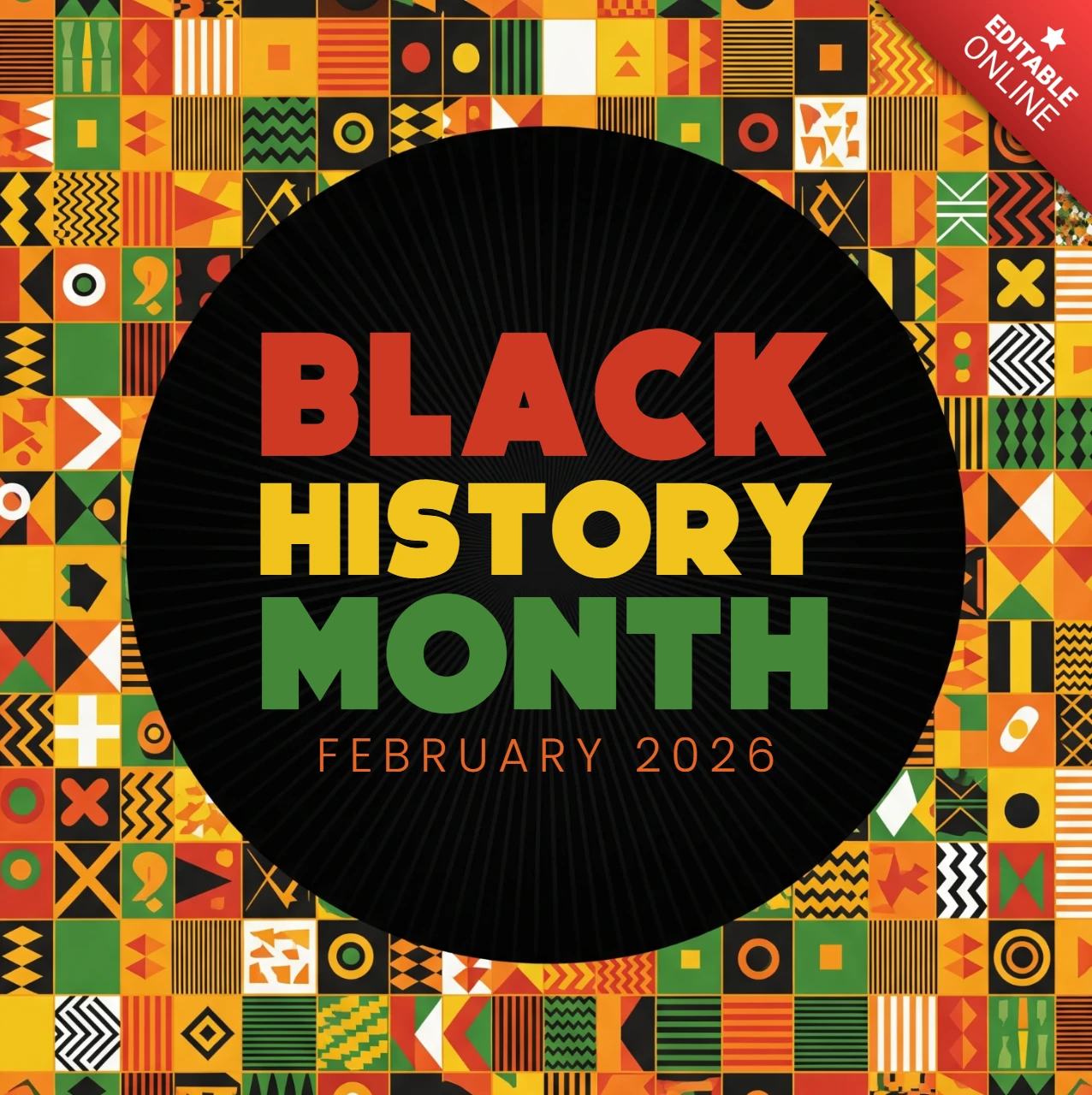
Affiche du mois de l'histoire des Noirs 2026 avec une typographie audacieuse dans des couleurs panafricaines, un cercle central et des bordures géométriques inspirées de l'Afrique célébrant l'héritage et la fierté.